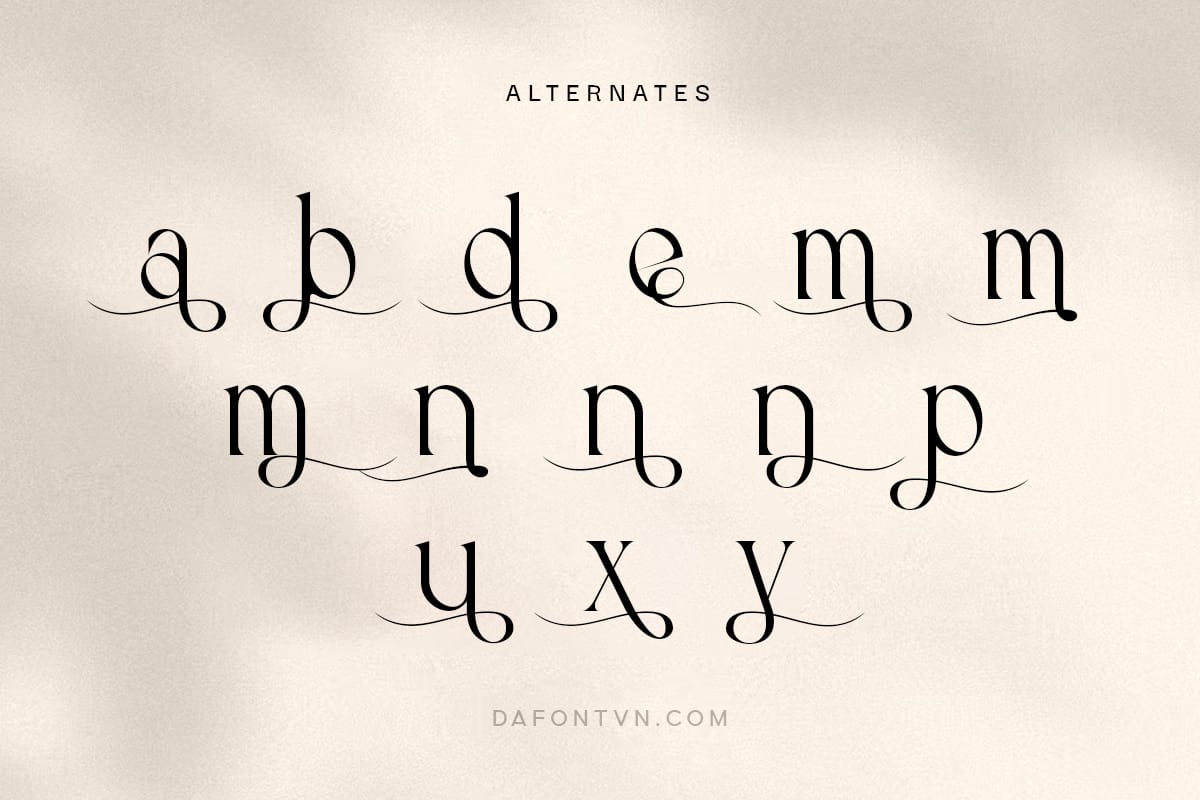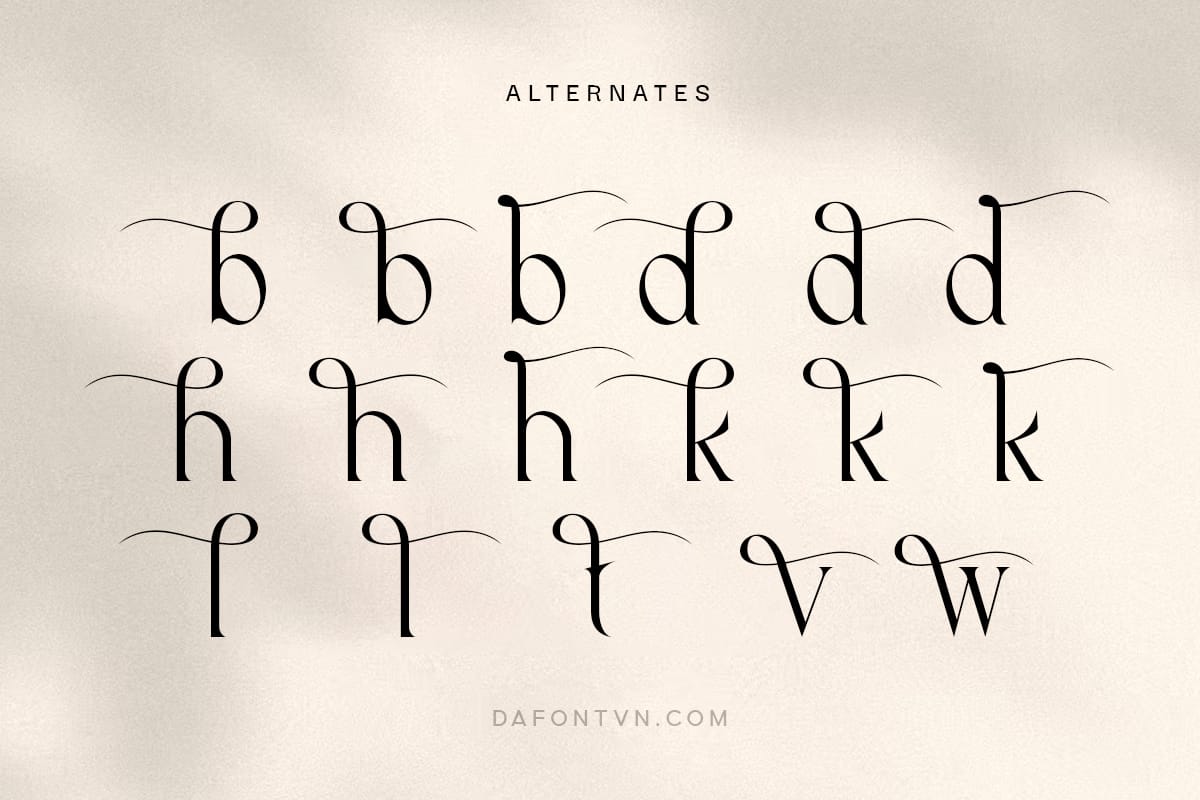
Xin giới thiệu đến các bạn 1 chiếc font việt hóa mới được ra mắt mang tên Kingdom – Một kiểu font ấn tượng, hiện đại và rất độc đáo.
Kingdom mang đến cho bạn những điểm nhấn ấn tượng bởi nó đi kèm với rất nhiều glyph đẹp cho cả chữ hoa và chữ thường vì vậy bạn có thể thỏa sức sáng tạo để có thể tạo ra nhiều thiết kế ấn tượng hơn.
Font được việt hóa tỉ mỉ, căn chỉnh từng dấu cho từng chữ, được kerning và mã hóa PUA cho phép bạn sử dụng dễ dàng trên bất kỳ phần mềm nào.